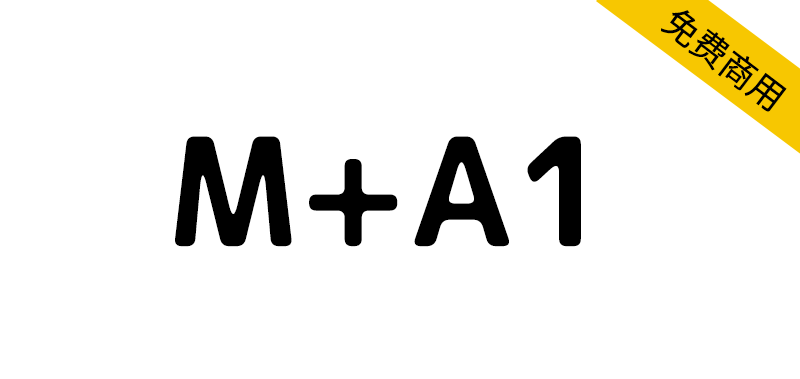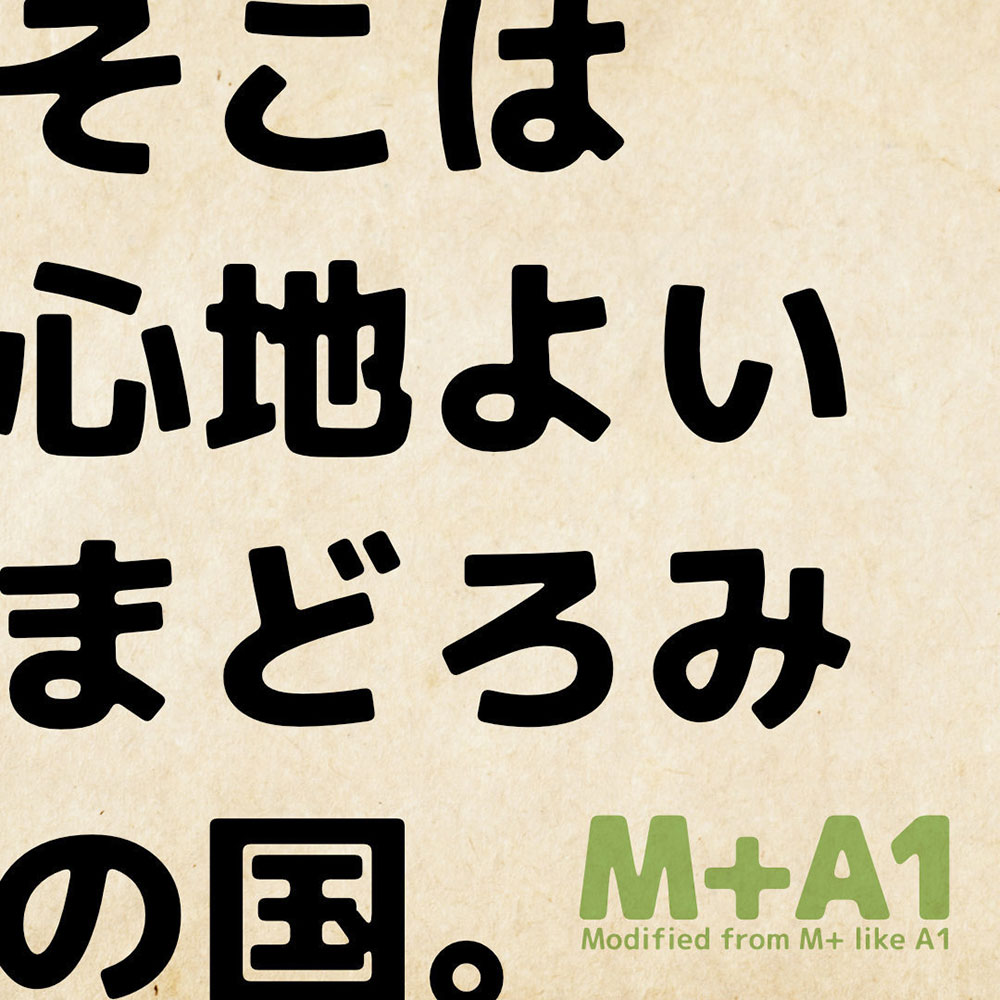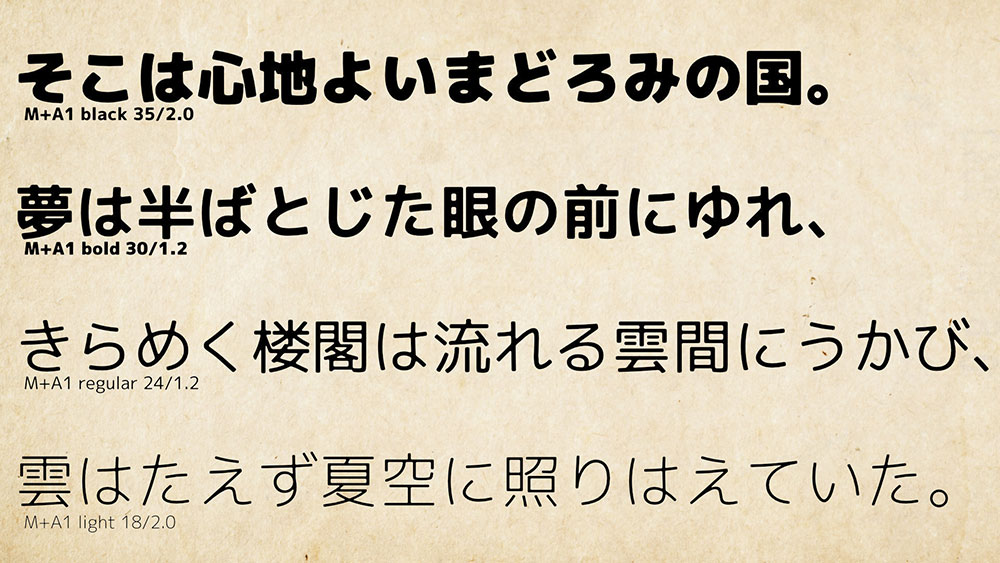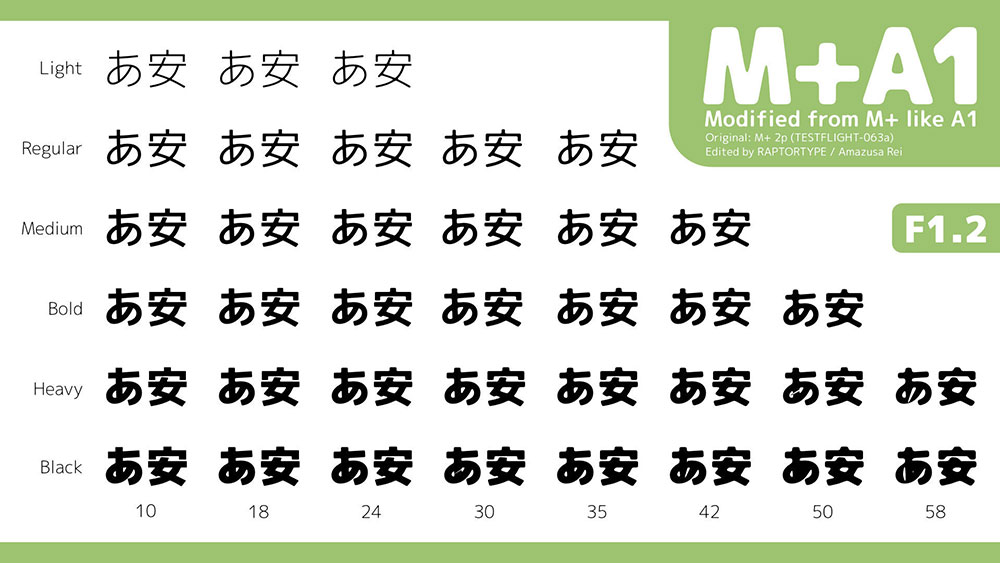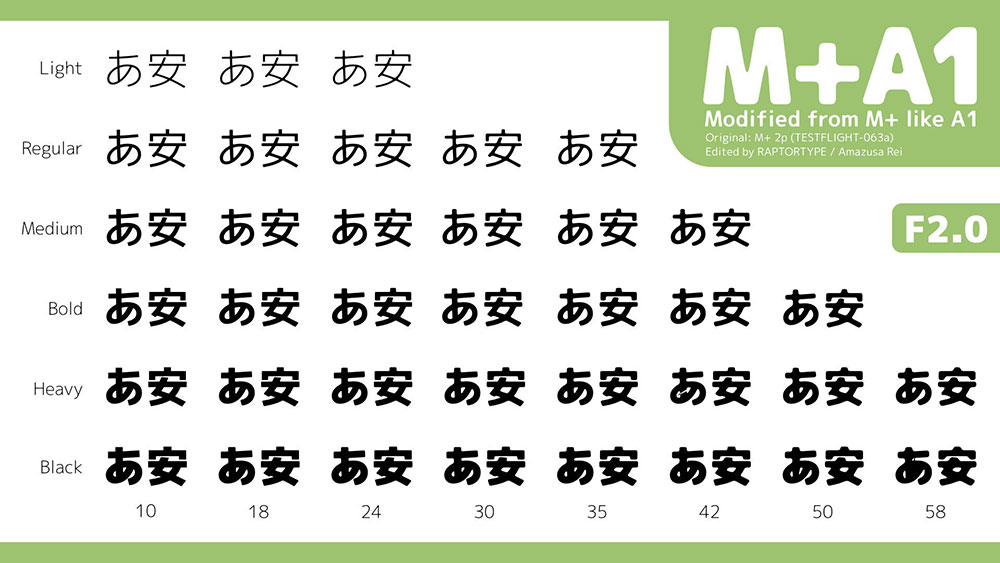
M+A1字体是对M+ FONTS进行修改,利用Python机械地进行了圆角、油墨汇集处理的字体。每个字体包含 8000 多个字符,共有74个版本。可商用,可重新发布、修改。由于机械性地编辑,一部分的文字崩塌了,使用的时候请注意。
「M+A1」フォントはM+ FONTSを改変し、Pythonにより機械的に角丸・墨溜まり処理を施した書体です。1フォント8000字以上の文字を収録、全74バージョンを用意しています。商用利用可。再頒布、改変可。※機械的に編集しているため、一部の文字が崩れています。使用の際にはご注意願います。